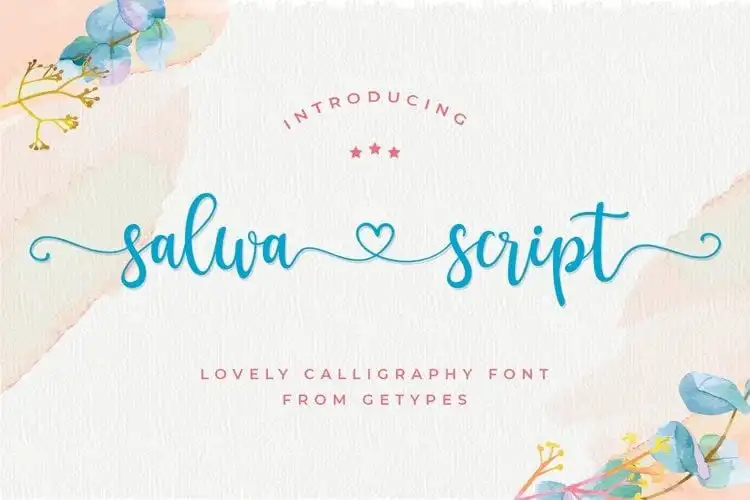
Salwa Calligraphy Font – Download Grátis
A Salwa Calligraphy Font é uma elegante fonte de escrita manuscrita desenvolvida por Getypes Studio, que foi projetada meticulosamente para se tornar um verdadeiro favorito. Com sua forma esguia e delicada, essa fonte possui um toque feminino e encantador, perfeitamente adaptável para aplicativos como marca de empresa, convites de casamento ou outros projetos românticos. Esta fonte PUA encodada lhe permite acessar todas as gílias e swashes com facilidade. Suas linhas finas e delicadas criam um equilíbrio perfeito, tornando-a uma escolha incrível para qualquer projeto que busque transmitir elegância ou romantismo de maneira discreta e sofisticada. Ideal tanto para profissionais quanto para amantes da arte gráfica, a Salwa Calligraphy Font é uma opção ideal para aqueles buscando uma fonte moderna e versátil para destacar em seus projetos. Sem sombra de dúvidas, ela se destaca como um recurso indispensável para qualquer designer ou criativo que busque adicionar sofisticação a suas criações digitais.